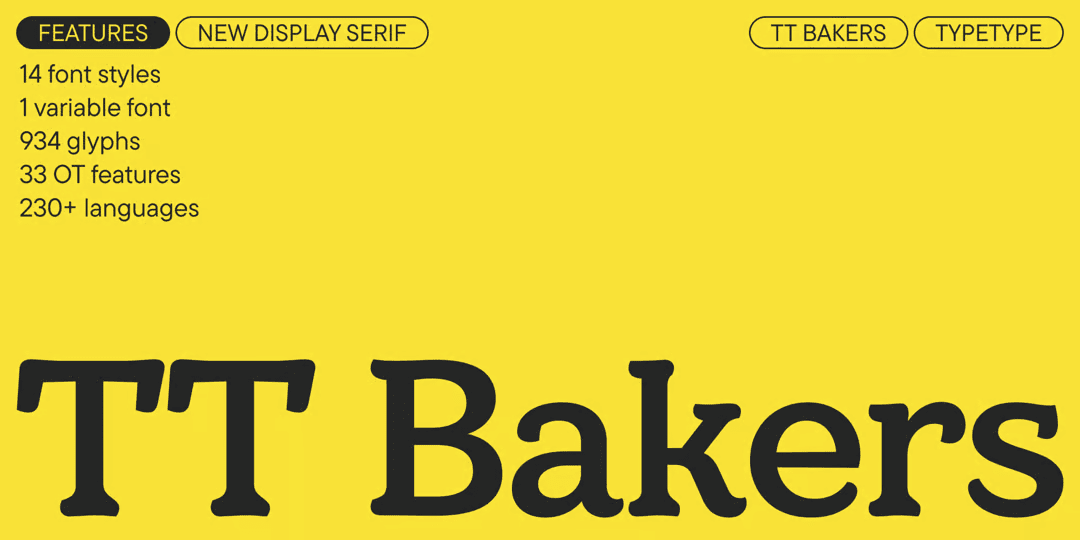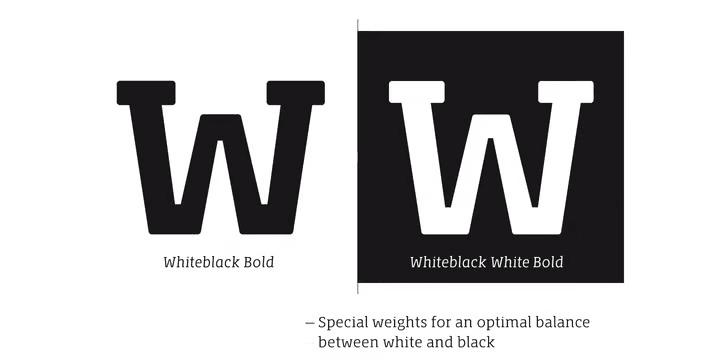
TT Bakers
本日は『なんとかの日』があまりにも大量に設定されているので完全に無視して(笑)こちら。可読性の良いスラブ?セリフ。ステムと同じような太さのセリフが付いているのだが、角が落とされて丸くなってたり筆のニュアンスのようなスッとしたトンガリが付いてたりでちょっと変わっている。まあ多分スラブセリフでいいと思う(強引)。グリフは結構素直なオールドスタイルで大変読みやすく、Display とはなっているが長文にも十分耐えられるだろう。オブリークタイプのイタリックもあって9ウェイトある他、バリアブルタイプもあり。キリル文字もサポート。
Whiteblack
ソフトでフレンドリーなスラブセリフ。コントラストが弱くxハイトやカウンターが大きくて大変視認性が良い。微妙にウェイトを太くした White というバージョンがあり、これは「暗い背景で白抜きにすると若干細く見える」現象を調整したもので、サインやディスプレイなど背景の色に応じで使い分けるとウェイトを揃えることができるようになっている。イタリックはほんの少しだけ傾いたオブリークタイプで、これもやはり書籍よりサイン用途を考慮してのものだろう。300種以上ものリガチャーを持っており、ブランディングなどにも使える。ノーマルと White それぞれに6ウェイトあって計24種。ただいま30%オフセール中。
Modet
カジュアルかつニュートラルでクセのないすっきりとしたヒューマニストサンセリフ。ややポップというかフレンドリーというか、そういう雰囲気のカジュアルなサンセリフで、可読性も大変良く日常使いには適したサンセリフ。a と g には1階建てと2階建てがあり、数字にはオールドスタイルもあり。ウェイトが太くなってもきちんと可読性は保たれており、なかなか優秀な書体である。イタリックがないのが残念だろうか。日用品のパッケージなどに。10ウェイト。